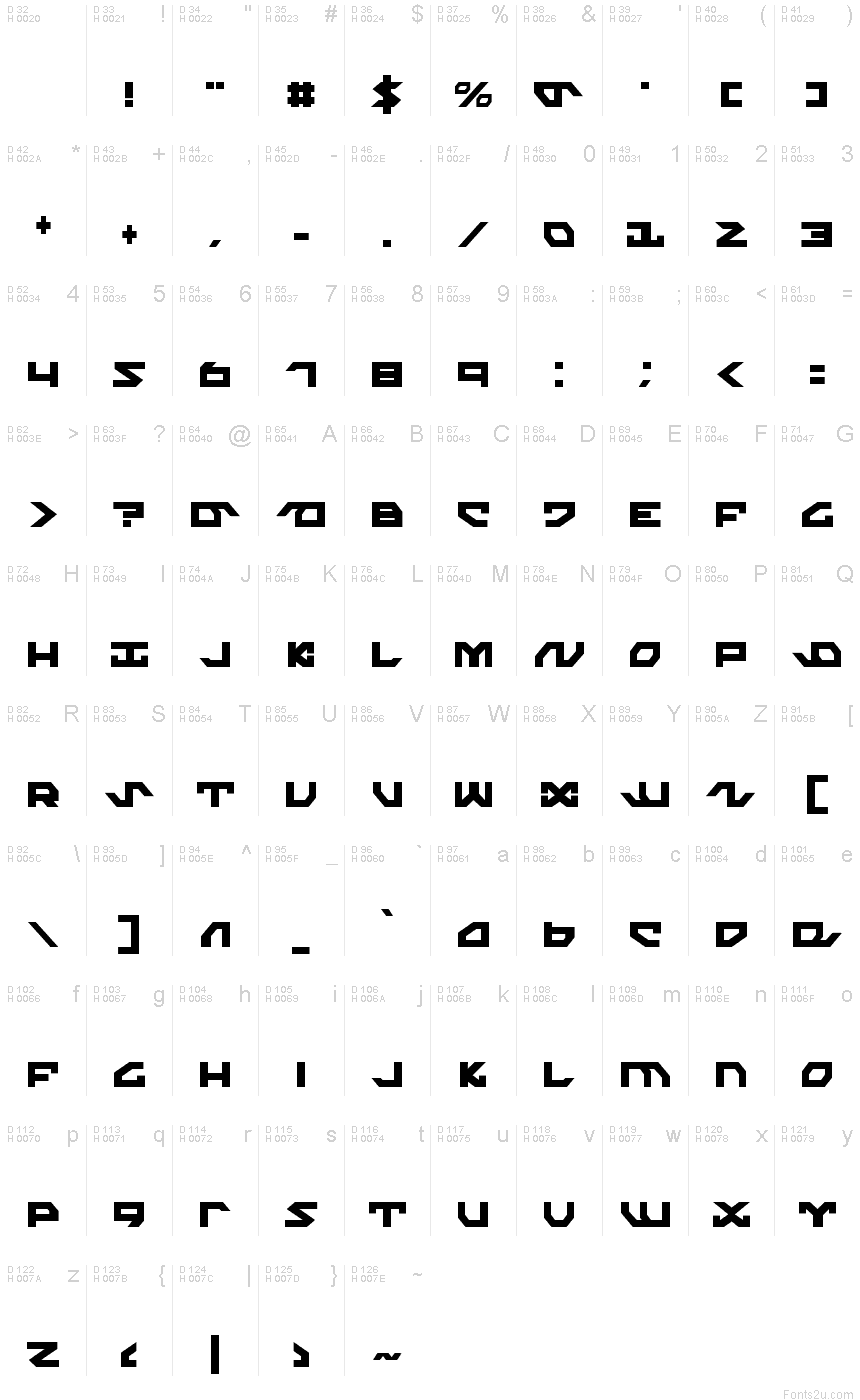
Nightrunner Condensed od Iconian Fonts to darmowy, futurystyczny font typu display w klimacie techno, zbudowany z ostrych kątów, ściętych przekątnych i masywnych wielkich liter, które kojarzą się z wyścigami arcade lub panelem kontrolnym w filmach sci-fi. Litery wyglądają na ciasno zaprojektowane i inżynieryjne, z głębokimi wcięciami i schodkowymi łączeniami, co nadaje krojowi szybki, mechaniczny rytm, nie tracąc przy tym wyrazistej sylwetki.
Naturalnie pasuje do logo gier, plakatów sci-fi, okładek albumów, tytułów i grafik streamingowych, wszędzie tam, gdzie krótkie słowa potrzebują cyfrowego, dynamicznego charakteru. Jako darmowy font świetnie sprawdzi się też na ulotkach wydarzeń lub w mocnych nagłówkach, zwłaszcza gdy szukasz kompaktowych liter, które można gęsto układać, zachowując ostre, maszynowe wykończenie.
Nightrunner Condensed